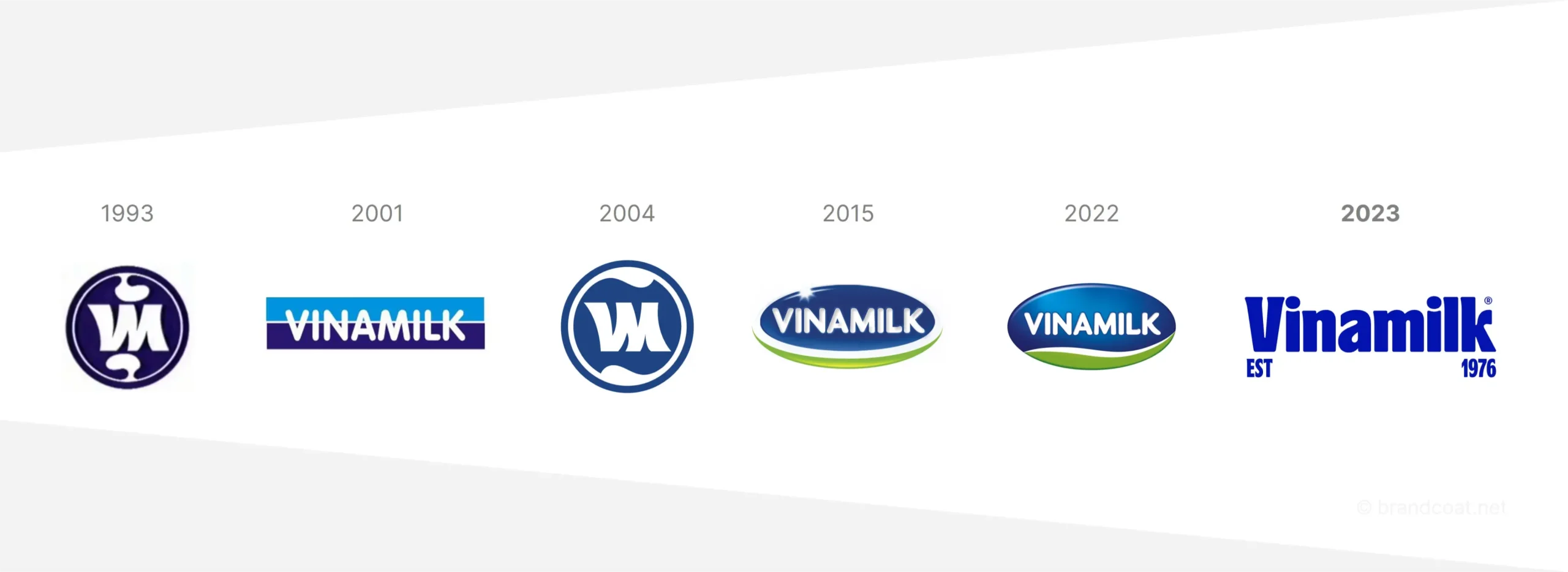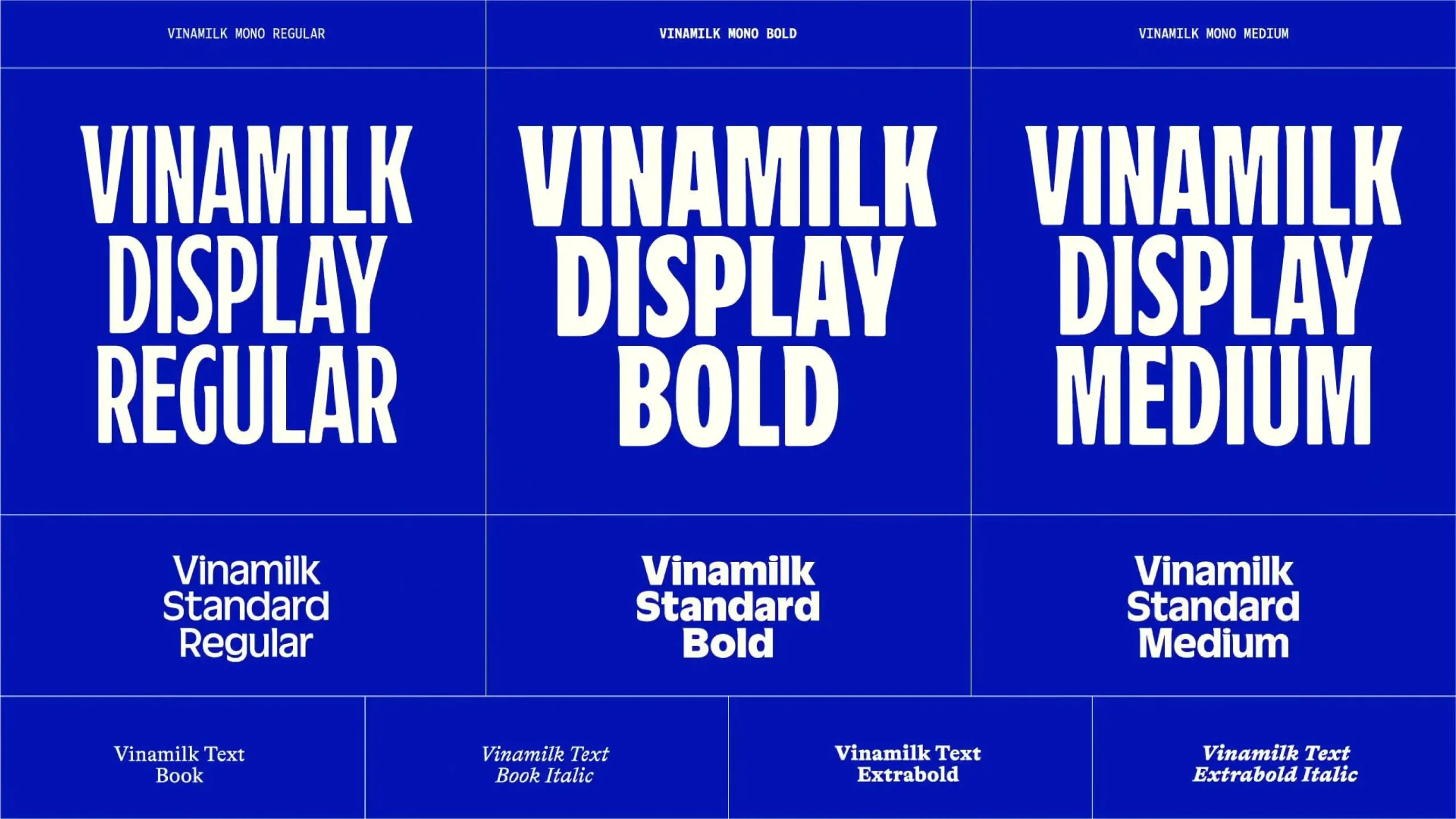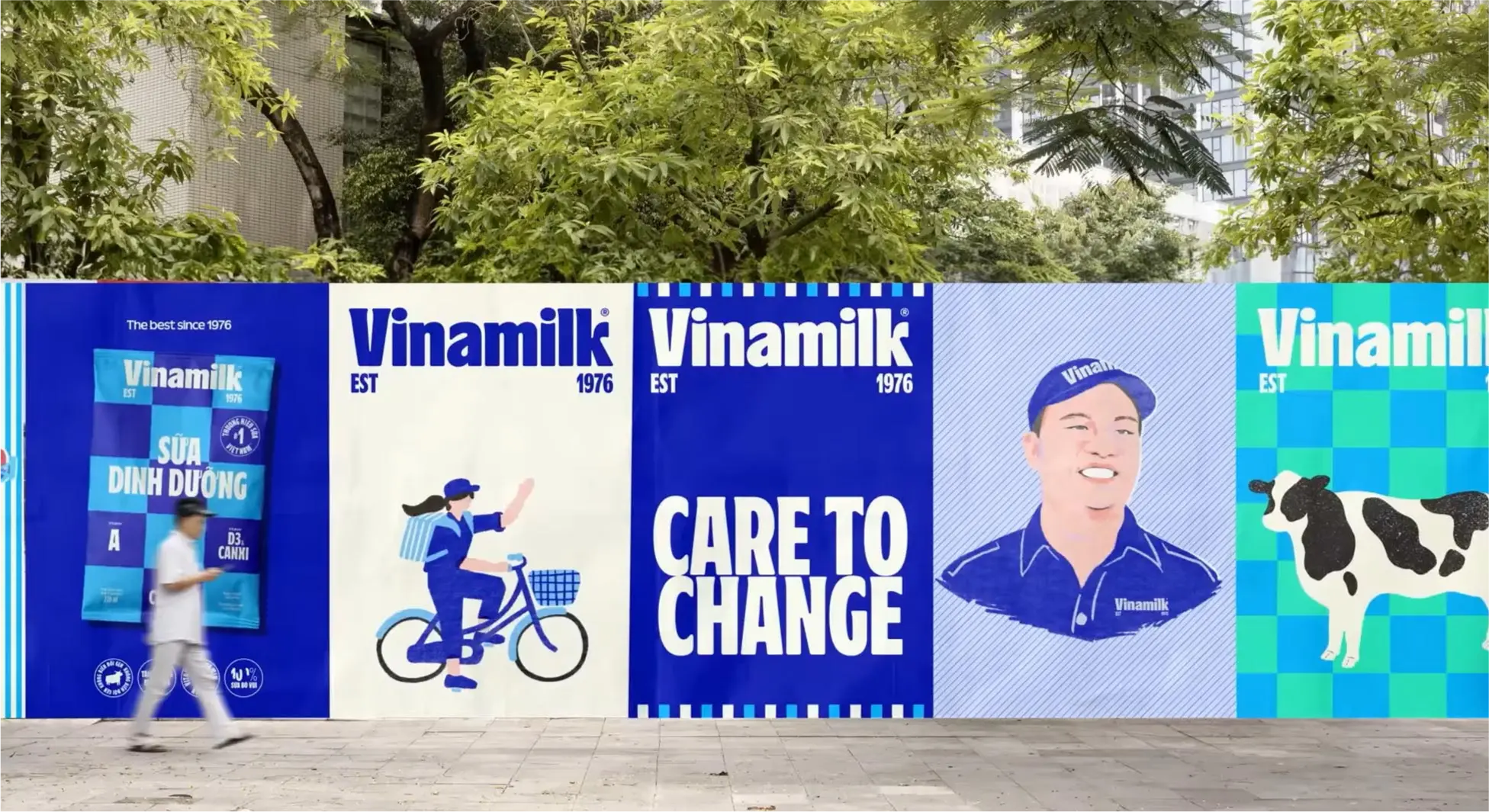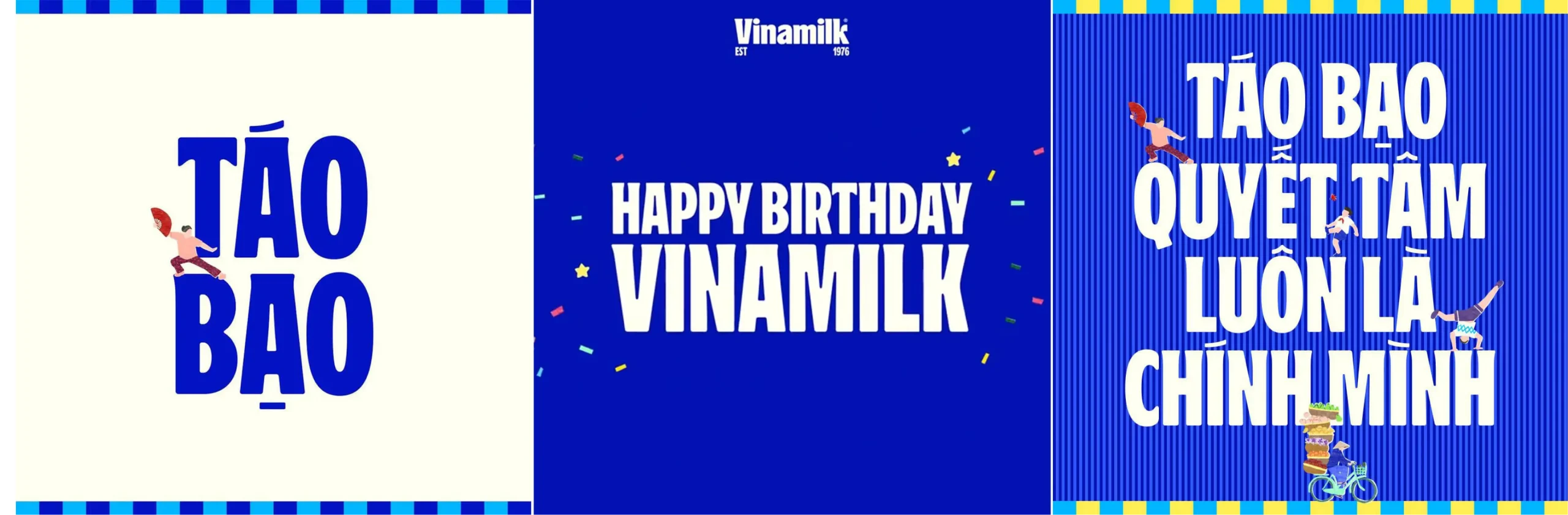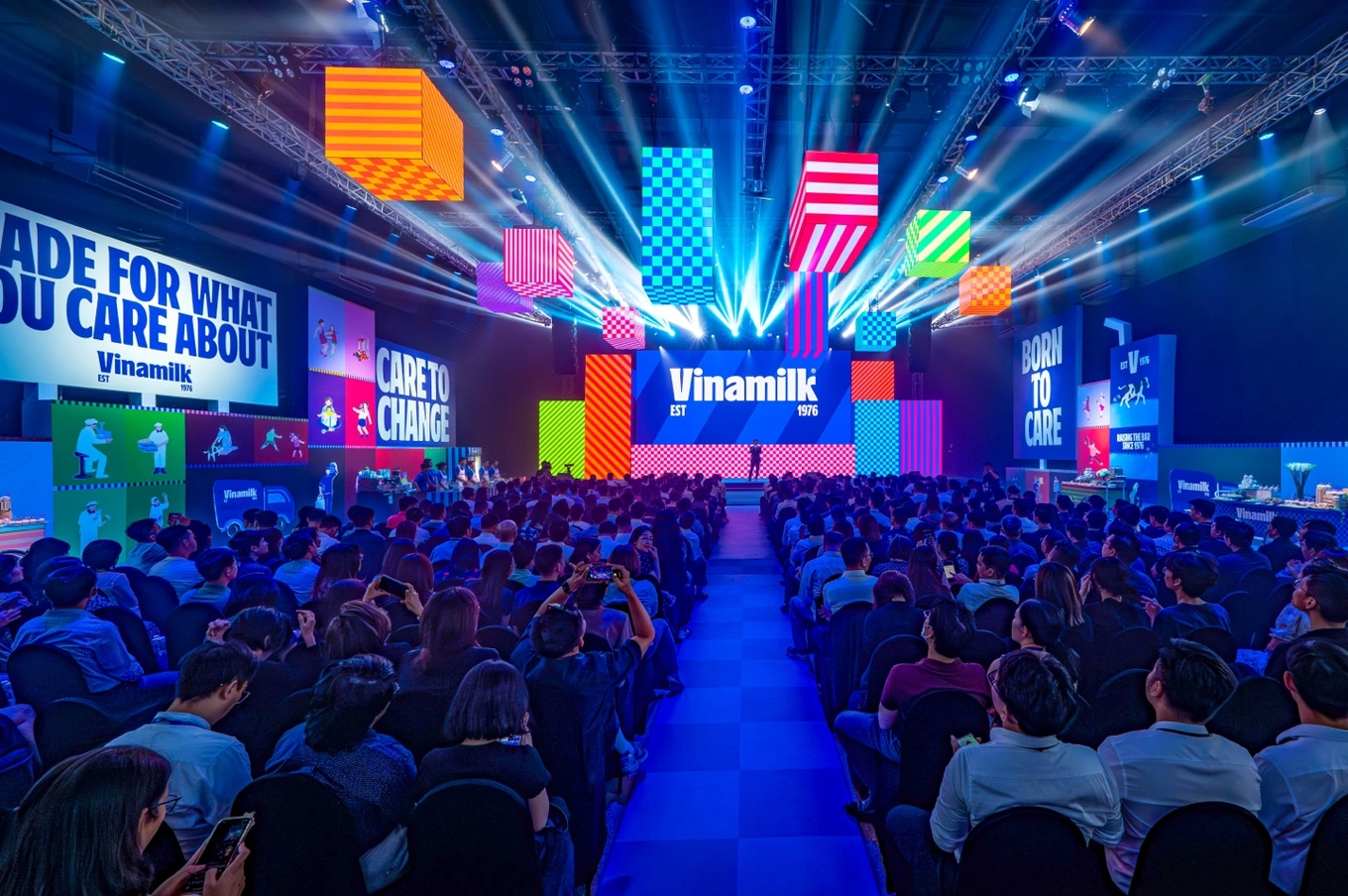
Vinamilk, thương hiệu sữa quốc dân của Việt Nam, đã tạo nên một cú hích truyền thông ngoạn mục với màn “tái định vị thương hiệu” đầy ấn tượng sau gần 5 thập kỷ gắn bó cùng người tiêu dùng. Điểm nhấn chính trong chiến lược này chính là sự thay đổi logo với font chữ đơn giản nhưng đầy tinh tế, thu hút sự chú ý và khơi gợi niềm thích thú của đông đảo cộng đồng mạng.
Về Vinamilk – giấc mơ sữa Việt
Vinamilk, thành lập năm 1976, là công ty sữa hàng đầu Việt Nam với hơn 20 nhà máy và trang trại trên khắp cả nước. Vinamilk cung cấp đa dạng các sản phẩm từ sữa tươi, sữa chua, phô mai, đến các sản phẩm dinh dưỡng cho trẻ em và người lớn, khẳng định vị thế thương hiệu uy tín và chất lượng hàng đầu.
Mặc dù trên thị trường có rất nhiều những tên tuổi lớn hay các thương hiệu sữa ngoại nhập khẩu nhưng Vinamilk vẫn giữ vững được vị thế của mình trong ngành Công nghiệp sữa tại Việt Nam. Với giá thành phải chăng, thơm ngon và dinh dưỡng, các sản phẩm sữa của Vinamilk đã trở thành một phần quen thuộc, nuôi dưỡng bao thể hệ trưởng thành và là một món “sữa quốc dân” mà hầu như ai cũng đã từng sử dụng.
Tái định vị thương hiệu năm 2023:
Ngày 6/7/2023, Công ty cổ phần Sữa Việt Nam (Vinamilk) đã chính thức công bố và đánh dấu bước tiến mới trong hành trình xây dựng thương hiệu. Dự án nhận diện thương hiệu của Vinamilk được dẫn dắt bởi đội ngũ sáng tạo đẳng cấp quốc tế : Megan Bowker (Giám đốc Sáng tạo của Vinamilk) phối hợp với chuyên gia chiến lược thương hiệu Karin Fyhrie của Sovereign Objects. Ngoài ra, hệ thống font chữ độc quyền mang tên VNM, được phát triển bởi sự hợp tác của Duy Dao (Studio DUY) và Yellow Type Foundry. Dự án tiên phong này bao gồm ba bộ chữ: VNM Display, VNM Standard và VNM Text, tạo nên một hệ thống typographic hoàn chỉnh, thể hiện rõ nét nhận diện thương hiệu Vinamilk với phong cách hiện đại và chuyên nghiệp.
1. Logo:
Điểm nổi bật đầu tiên trong logo mới của Vinamilk chính là sự thay đổi từ dạng phù hiệu (emblem) sang dạng Wordmark Logo. Thay vì sử dụng hình ảnh logo bầu dục có hình ảnh biểu tượng của bãi cỏ xanh lục và bầu trời xanh lam với dòng chữ Vinamilk ở giữa, logo mới chỉ tập trung vào phần chữ “Vinamilk” theo font chữ “Độc quyền” và ký hiệu “EST” và “1967″ – là năm ra đời của thương hiệu sữa này . Theo nhận định của các chuyên gia thiết kế, logo mới toát lên vẻ hiện đại, trẻ trung và tạo dấu ấn riêng biệt, giúp Vinamilk trở thành thương hiệu sữa duy nhất sở hữu kiểu chữ độc quyền này.
2. Màu sắc:
Màu xanh dương được sử dụng làm màu sắc chủ đạo cho logo mới, tượng trưng cho sự tin cậy, an toàn và cam kết về chất lượng sản phẩm của Vinamilk. Màu xanh dương cũng gợi lên cảm giác về bầu trời bao la, đại dương rộng lớn, thể hiện khát vọng vươn xa, chinh phục những đỉnh cao mới của Vinamilk.
3. Font chữ VNM hiện đại:
Font chữ VNM được thiết kế riêng biệt cho logo mới, thể hiện sự chuyên nghiệp, sự giao thoa giữa truyền thống và thiết kế hiện đại và phù hợp với định vị thương hiệu của Vinamilk. Tuy nhiên, sự đổi mới này không chỉ dừng lại ở các kiểu chữ tùy chỉnh; nó còn vượt xa hơn với các cách tiếp cận và bố cục Typographic tinh tế. Ngôn ngữ hình ảnh của VNM giờ đây hấp dẫn hơn nhờ những phông chữ sáng tạo này thể hiện đầy đủ cá tính của thương hiệu. Bạn có thể dễ dàng thấy sự đồng nhất của font chữ được thể hiện trong bộ nhận diện thương hiệu như bao bì, trang web giúp Vinamilk dễ dàng được nhận diện và ghi nhớ bởi khách hàng.
– VNM Display: Font chữ hiển thị nổi bật, sử dụng cho tiêu đề, bảng hiệu, logo,…
– VNM Standard: Font chữ tiêu chuẩn, ứng dụng cho văn bản chính trong các ấn phẩm, tài liệu,…
– VNM Text: Font chữ dành cho văn bản dài, dễ đọc, đảm bảo sự thoải mái cho người xem
Tác động tích cực đến thương hiệu của việc tái định vị thương hiệu Vinamilk năm 2023
Việc ra mắt font chữ VNM trong chiến lược tái định vị thương hiệu năm 2023 của Vinamilk đã mang lại nhiều lợi ích to lớn, góp phần củng cố vị thế thương hiệu hàng đầu Việt Nam và khẳng định tầm nhìn chiến lược sáng suốt của Vinamilk.
1. Tăng cường nhận diện thương hiệu:
Font chữ VNM được ứng dụng thống nhất trên mọi ấn phẩm, từ bao bì sản phẩm, website, đến các ấn phẩm quảng cáo, truyền thông. Nhờ vậy, Vinamilk tạo dựng được hình ảnh thương hiệu chuyên nghiệp, đồng nhất và dễ dàng nhận diện trong tâm trí người tiêu dùng. Ngoài ra, việc thay đổi bộ nhận diện thương hiệu nhằm mục đích thổi một luồng gió mới, mang những năng lượng tích cực, trẻ trung để người tiêu dùng sẽ ngày càng tin tưởng Vinamilk.
2. Nâng tầm giá trị thương hiệu:
VNM không chỉ là một font chữ đơn thuần mà còn là biểu tượng cho sự hiện đại, tinh tế và đẳng cấp của Vinamilk. Việc sử dụng font chữ VNM thể hiện sự đầu tư bài bản, trau chuốt của Vinamilk vào hình ảnh thương hiệu, từ đó nâng cao giá trị thương hiệu trong mắt khách hàng.
3. Gắn kết cộng đồng:
Chiến dịch cho phép người dùng tự tạo logo tên mình theo phong cách Vinamilk đã tạo nên trào lưu thú vị trên mạng xã hội, thu hút sự tham gia đông đảo của cộng đồng. Đây là chiến lược marketing hiệu quả, giúp Vinamilk tiếp cận khách hàng tiềm năng, lan tỏa hình ảnh thương hiệu rộng rãi và gia tăng mức độ tương tác với khách hàng.